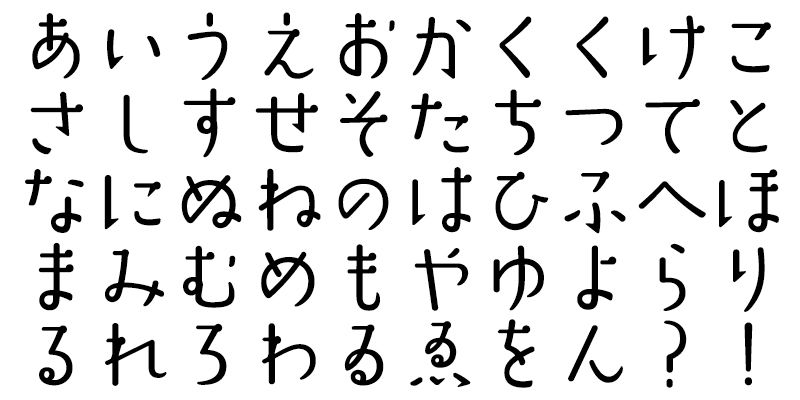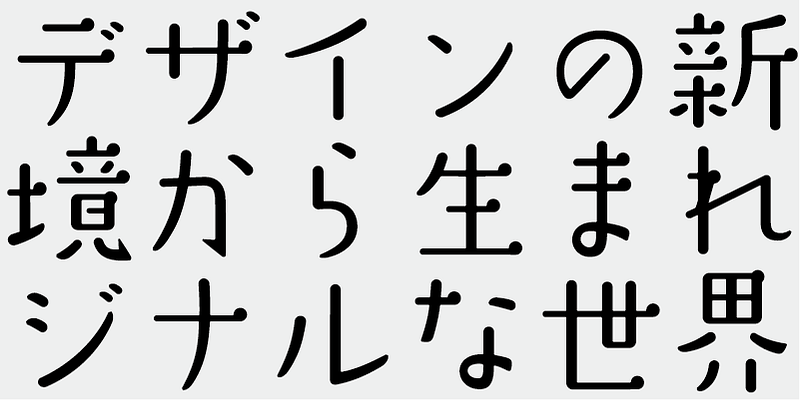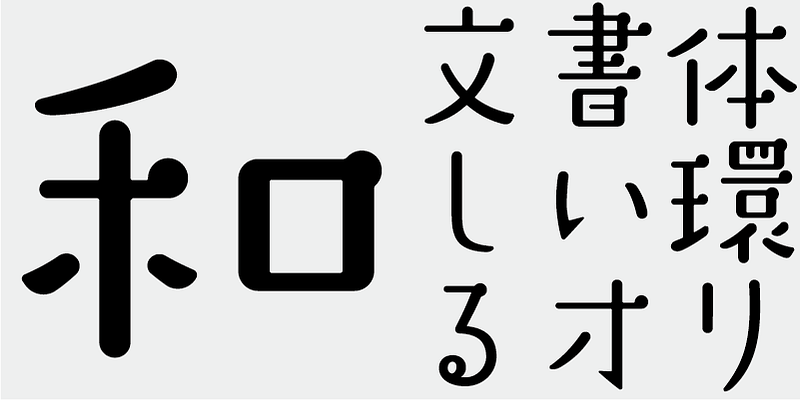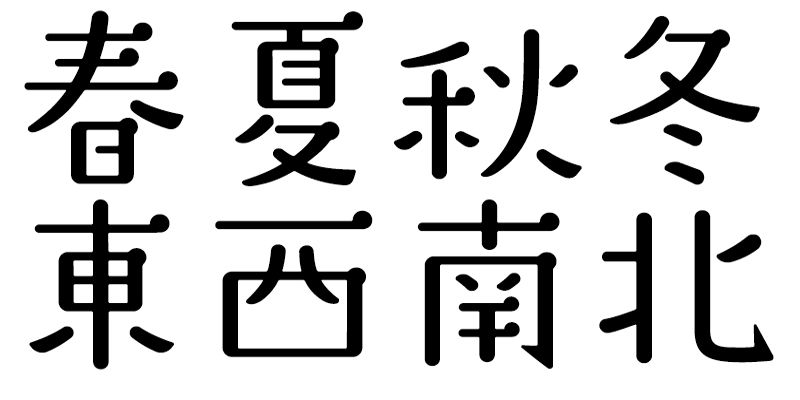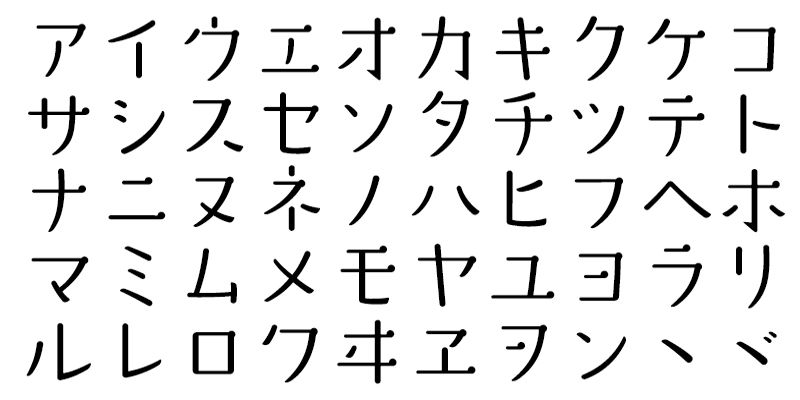
Une conversation fluide. Un ciel clair. Un pique-nique. Mayuminwalk a été conçu pour faire revivre ces belles énergies.
Cette police comprend les 1 000 principaux caractères kanji, choisis dans les tables de fréquence des caractères établis par les sociétés de presse, les maisons d’édition et les instituts de recherche linguistique, ainsi que 206 caractères kana et signes de ponctuation.
Dans la production de polices japonaises d’aujourd’hui, les 7 000 caractères de la norme JIS sont considérés comme essentiels. Mais toutes les polices ont-elles vraiment besoin de 7 000 caractères ? À l’ère de la phototypie, on utilisait beaucoup moins de caractères. FONT1000, un groupe de typographes indépendants, a commencé par se focaliser sur cette simple question. Nous avons sélectionné le minimum de 1 000 caractères kanji (idéographiques) nécessaires pour la composition en japonais et créé activement des polices pour les prendre en charge. Ce jeu de 1 000 caractères kanji a été créé en étudiant des données de fréquence des caractères compilées par des sociétés de presse, des maisons d’édition et des organismes de recherche linguistique, etc. Il comprend également des caractères syllabiques kana et des signes de ponctuation. FONT1000 a été créée en 2001 avec 25 designers et 25 polices de caractères. Aujourd’hui, nous avons 130 polices et comptons désormais près de 40 membres, ce qui permet de travailler sur des polices avec plus de caractères.